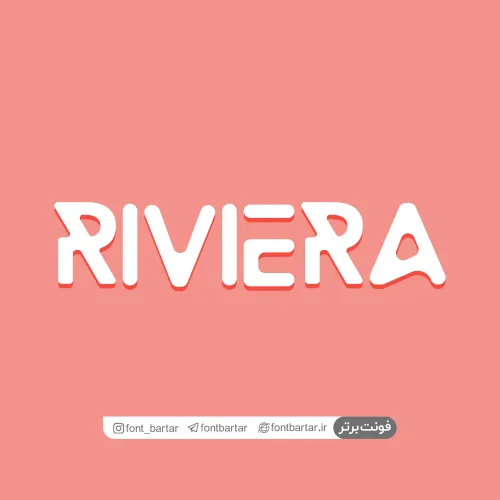
فونت انگلیسی Riviera
فونت انگلیسی Riviera ، یک فونت انگلیسی بسیار زیبا می باشد. از این فونت زیبا می توانید در طراحی پوستر، تیشرت، لوگو و … استفاده کنید. این فونت با فرمت otf برای شما دوستان قرار داده شده است. تمامی حروف و اعداد این فونت را می توانید در تصاویر پیش نمایشی که برای شما دوستان قرار دادیم مشاهده کنید. فونت انگلیسی Riviera کاملا رایگان است.